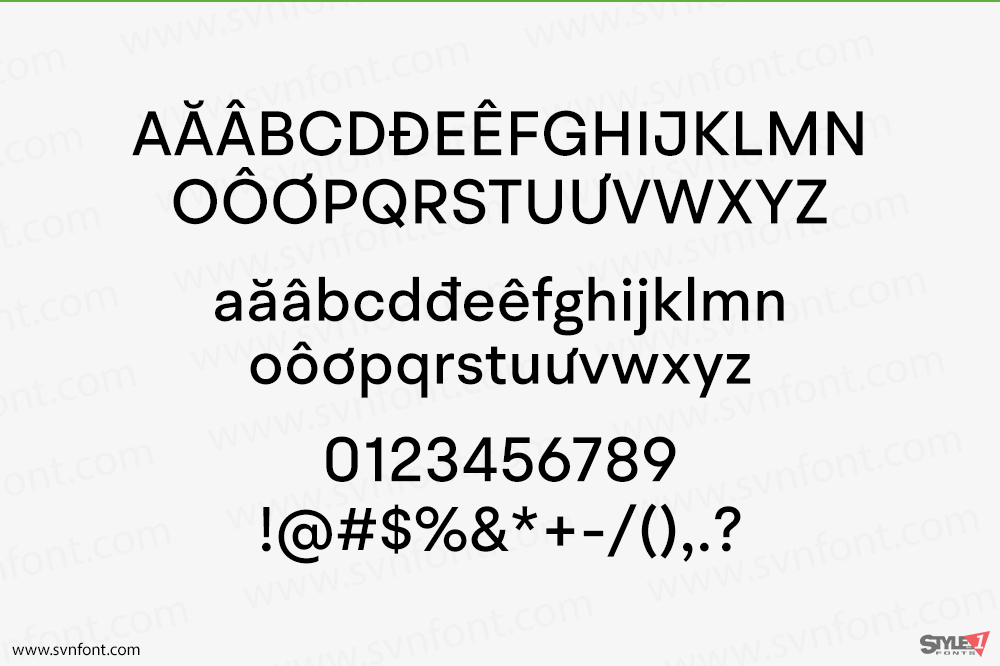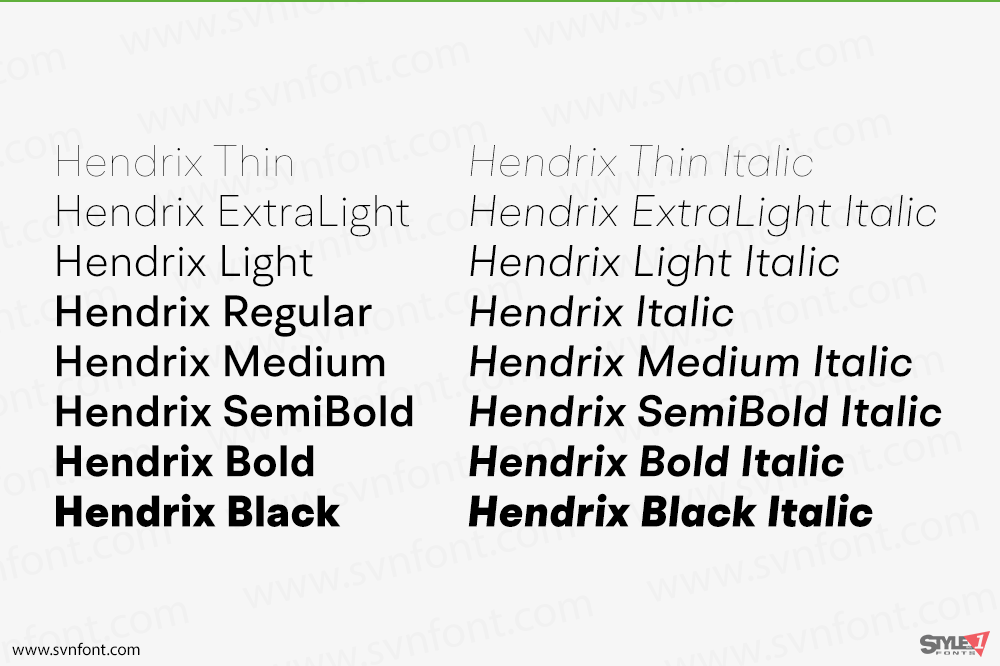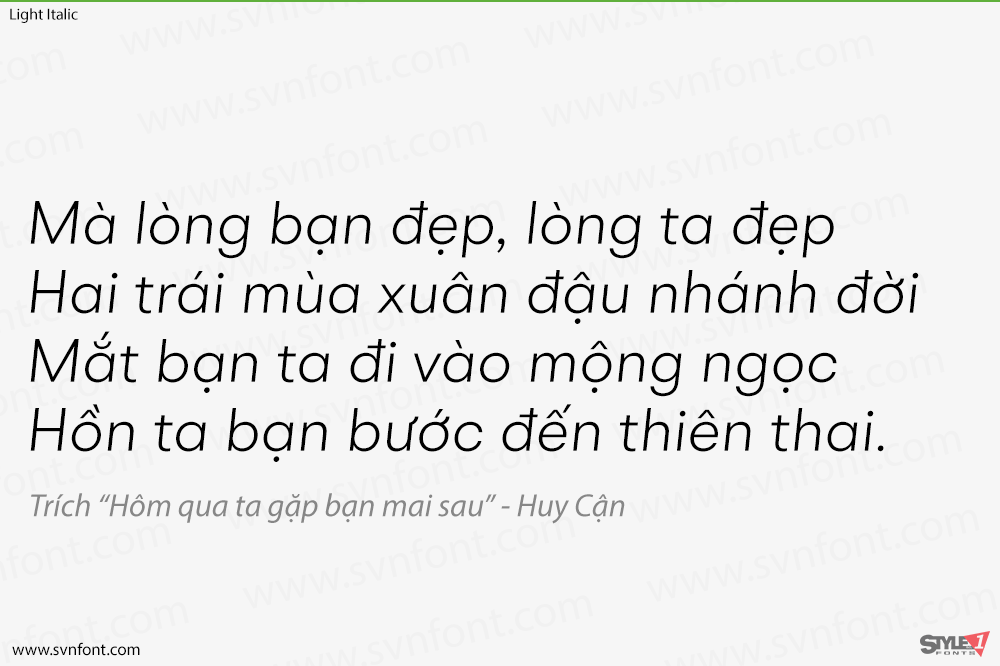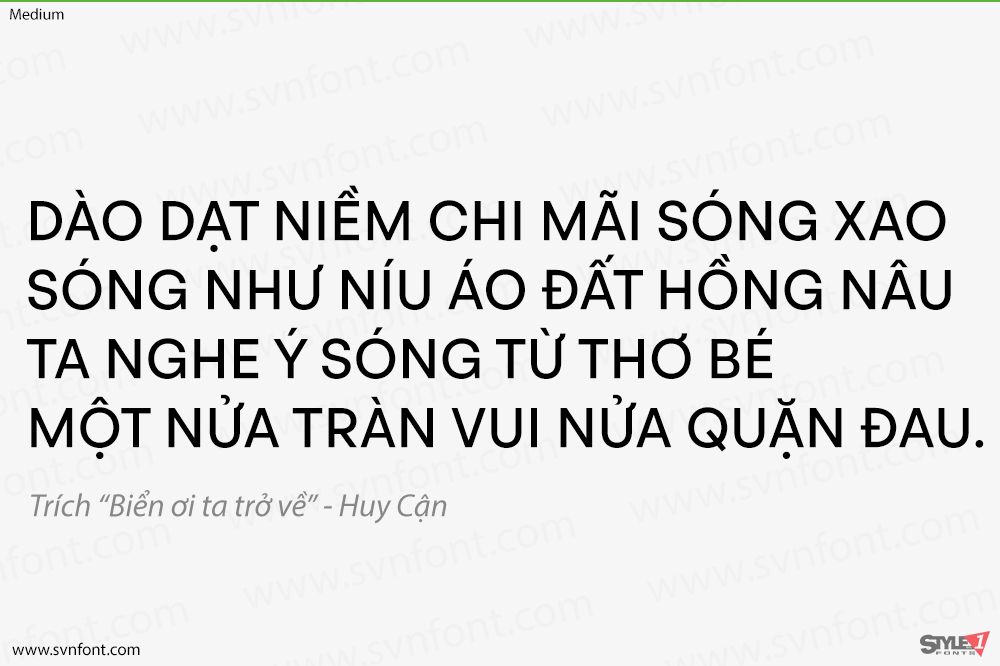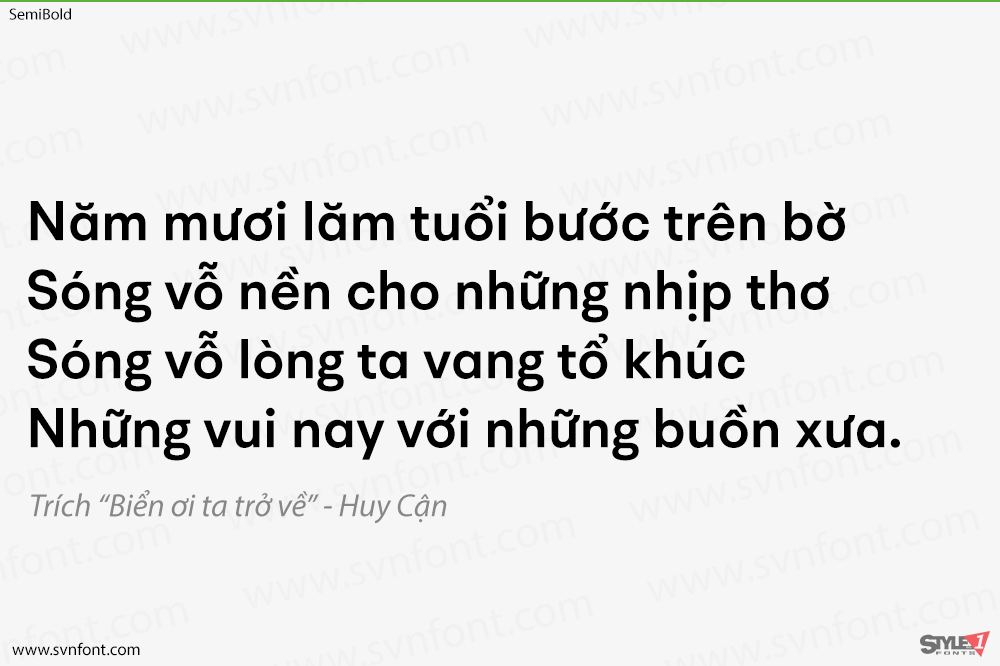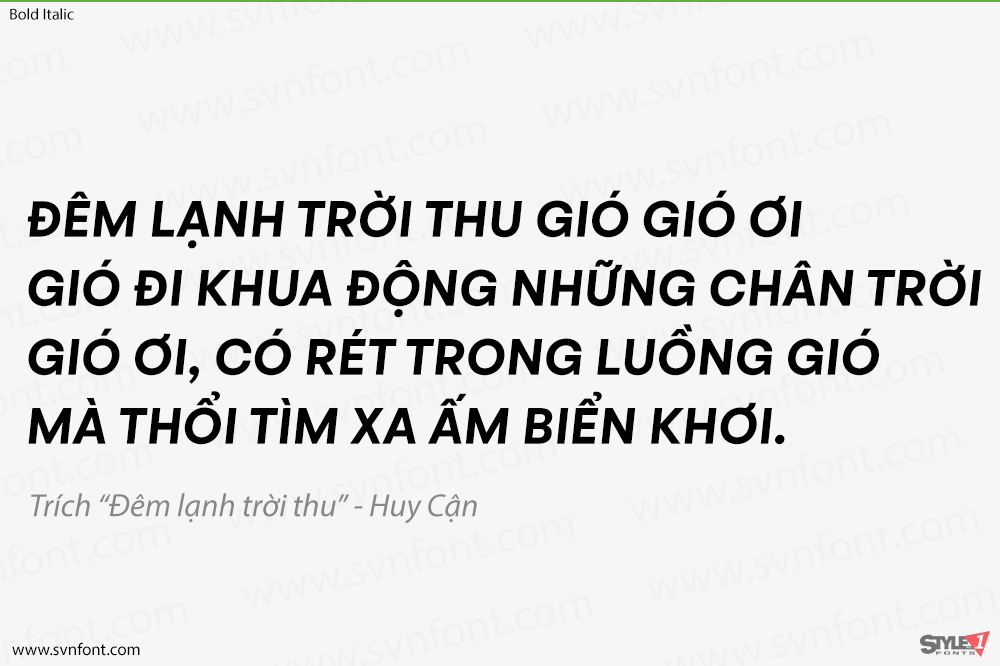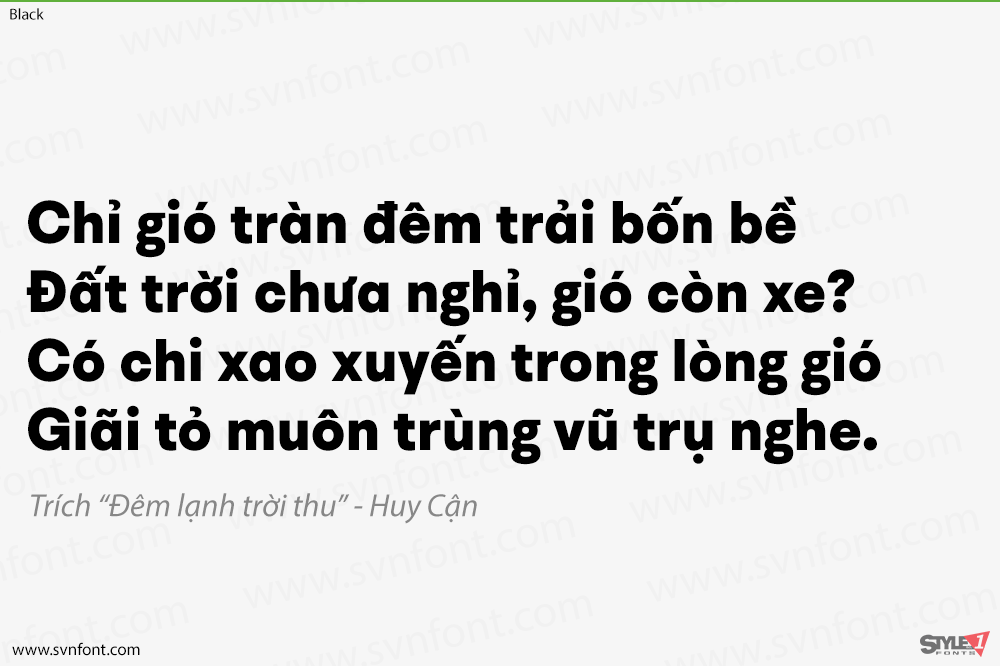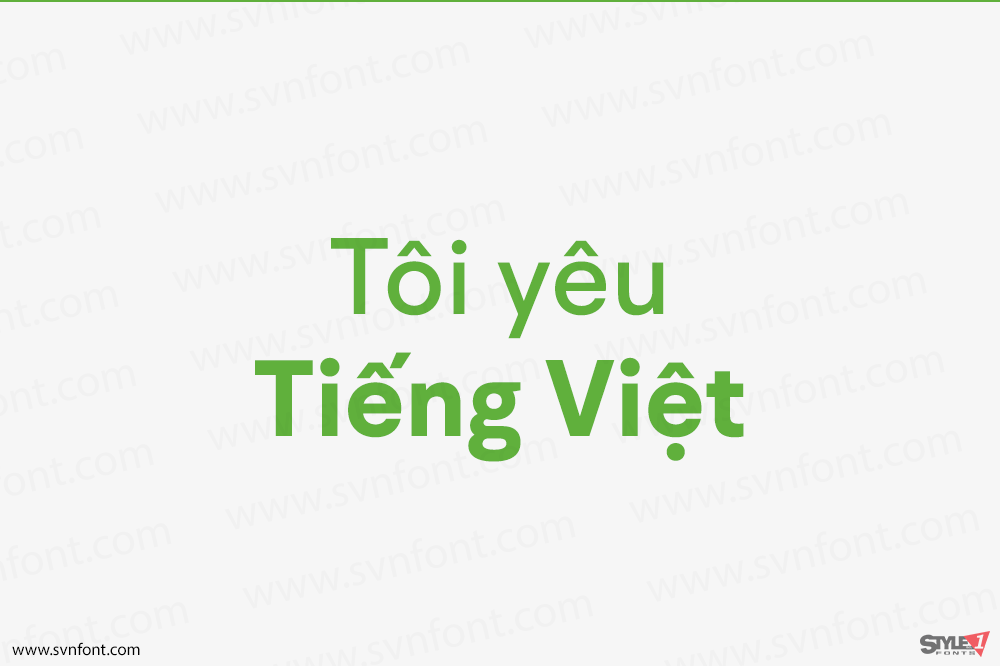
Một họ kiểu chữ grotesque hình học hiện đại gồm 16 kiểu dáng. BR Hendrix là sự cân bằng tinh tế giữa chức năng và các đặc điểm đương đại. Được vẽ chính xác với thẩm mỹ hiện đại trong tâm trí, Hendrix có những phẩm chất quen thuộc liên quan đến các kiểu chữ grotesque cổ điển, nhưng kết hợp chúng với một hương vị hình học mạnh mẽ hơn.
BR Hendrix cung cấp hỗ trợ kiểu chữ nâng cao với các tính năng như các dạng chữ nhạy cảm với chữ hoa/thường (case sensitive forms), phân số (fractions), số không gạch chéo (slashed zeros) và nhiều bộ chữ số khác nhau (multiple figure sets).
Nhà thiết kế: Christoph York
Nhà phát hành: Brink